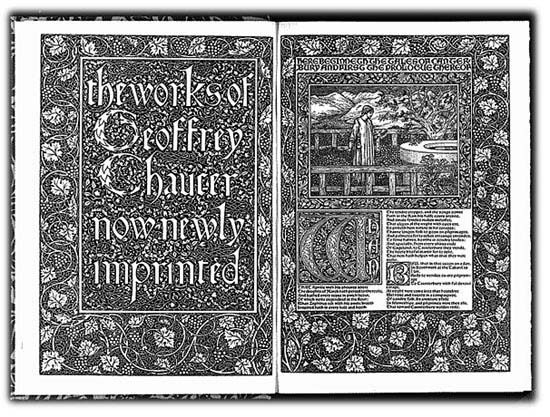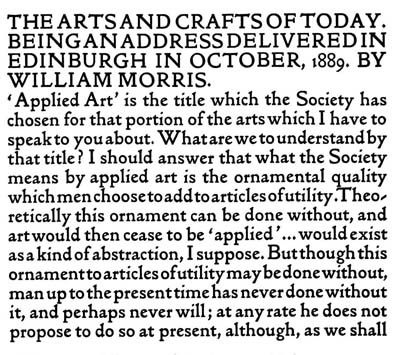
William Morris (1834–1896)
Foi um dos incuráveis neo-românticos da sua época, liderou um revivalismo na Inglaterra victoriana e capitalista, baseado nas artes e ofícios da idade medieval. Foi o inspirador-mestre do Arts and Crafts Movement.
W. Morris teve uma profunda influência nas artes visuais e no desenho industrial dos fins do século XIX. Sobre o desenho tipográfico, Morris propagava: “Letters should be designed by artists, not by engineers”.
Com o seu paradigma saudosista da Idade Média, Morris quis reafirmar a primazia da qualidade do trabalho manual sobre a máquina industrial da era do Imperialismo.
Morris associou a produção mecânica ao sistema capitalista e, por conseguinte, pensava que a revolução socialista deteria a mecanização do trabalho e substituiria os grandes aglomerados urbanos por pequenas comunidades, onde os objectos de utilidade seriam produzidos por processos artesanais.
Condenou o sistema económico de seu tempo e refugiou-se na contemplação da Idade Média, quando “cada homem que fabricava um objecto fazia ao mesmo tempo uma obra de arte e um instrumento útil.”
Liderou o movimento das pequenas imprensas privadas no Reino Unido, que integrou famosas oficinas como Vale, Eragny, Essex House e Dove.
A sua produção librária-tipográfica centrou-se na famosa Kelmscott Press, fundada em 1891.
Em 1883 fundou a Federação Socialdemocrata, e mais tarde, a Liga Socialista, tentando contrariar com a sua política utopista a orientação marxista do movimento operário dos fins do século XX. Entre as obras que escreveu, destaca-se a novela utópica Tales from Nowhere.
William Morris nasceu no ano de 1834 em Walthamsow (Inglaterra). Em 1848, iniciou os seus estudos no Marlborough College, que completou no Exeter College de Oxford, onde estudou arquitectura, arte e teologia.
Morris começou a trabalhar em 1856 no estúdio de arquitectura de G.E. Street; nos anos seguintes trabalhou como pintor profissional (1857-62).
Com a experiência adquirida em arte e arquitectura, fundou em 1861 a empresa Morris, Marshall, Faulkner & Co., vocacionada à arquitectura e ao desenho industrial (hoje: product design). Em 1875, a companhia passou a chamar-se Morris & Co., sendo Morris o único propietário.
Palestra de Morris
William Morris começa a desenvolver uma prolífica actividade como artista-artesão, desenhador, impressor, poeta, escritor, activista político, sempre tentando preservar as artes e ofícios medievais, sempre em guerra com a produção em massa, típica do modo de produção industrial e capitalista.
Na sua famosa Kelmscott Press, fundada em 1891, produziu trabalhos como, por exemplo, The Story of Sigurd the Volsung, The fall of the Nibelungs.
Também foram editados autores clássicos, sendo mais conhecida a obra-prima The Works of Geoffrey Chaucer, um in-folio de 556 páginas que foi ilustrado com xilogravuras segundo desenhos do artista Burne-Jones e impressa na Kelmscott Press em 1896, ano da morte de W.M.
Para desenhar e imprimir estas obras, Morris estudou em detalhe, entre outros, as iniciais e os bordes de Peter Löslein e Bernhard Maler, artistas que trabalharam para o prototipógrafo alemão Erhard Ratdolt (1474-84).
Após a morte de Morris, o movimento das private presses (oficinas de imprensa particulares) intensificou-se em Inglaterra. A Essex House Press de Ashbee adquiriu os prelos Albion da oficina de Morris e contratou alguns empregados da Kelmscott Press.
Kelmscott Press Chaucer
Morris influenciou typeface designers contemporâneos, como Edward Johnston e Eric Gill.
Fontes que Morris desenhou
• O tipo Kelmscott Golden (1889-1890), inspirad0 na letra de Nicolas Jenson. Este tipo Golden foi produzida em colaboração com o gravador de punções Edward Prince (que elaborou tipos para várias imprensas privadas da época) e o impressor Emery Walker.
• A fonte Troy (1891-1892) foi baseada no tipo gótico de Schöffer, Zainer e Koberger.
• A Chaucer (1892) é um redesign do tipo Troy e foi utilizada nas páginas de The Chaucer.